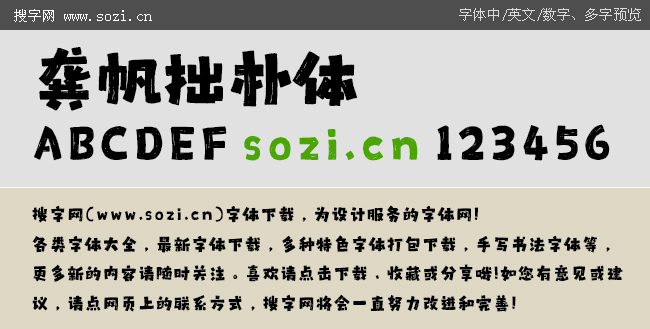
龔帆拙樸體
搜字網(wǎng)給大家提供一款龔帆拙樸體中文字體下載,該字體是一款非常個(gè)性的藝術(shù)字體,字體古樸自然,帶有筆刷效果,給人一種可愛的視覺感受,適用于平面宣傳設(shè)計(jì)、網(wǎng)頁設(shè)計(jì)、海報(bào)設(shè)計(jì)等應(yīng)用(淘寶搜龔帆字庫可買單字授權(quán))。